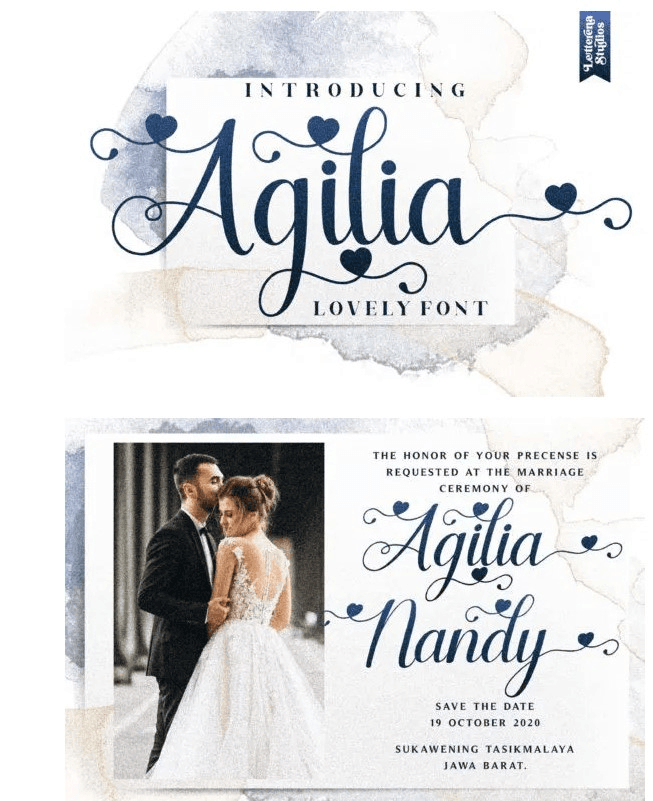
Agilia Font
Agilia - это стильный и нежный рукописный шрифт.
У него чистая, тонкая и гладкая атмосфера, и он станет хитом для любого дизайна, к которому вы хотите его добавить. Этот шрифт закодирован PUA, что означает, что вы можете легко получить доступ ко всем глифам и штрихам!